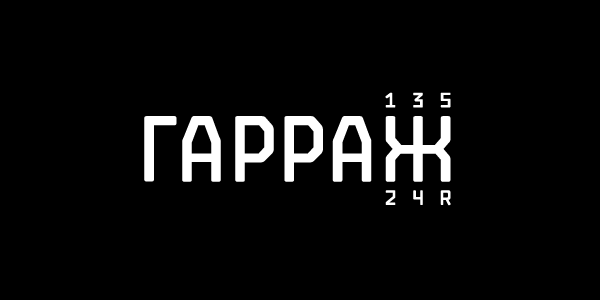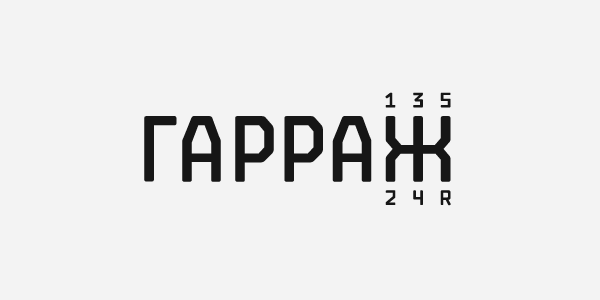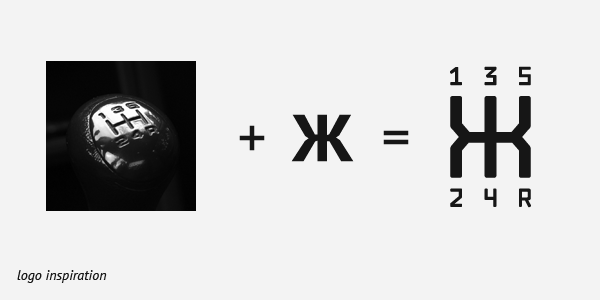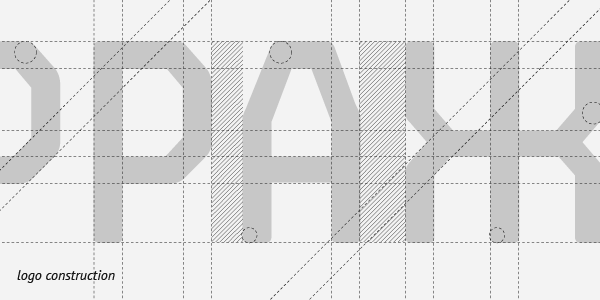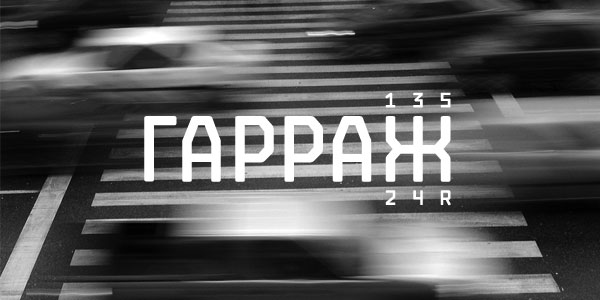
Гарраж
Логотип для пермского автомобильного сайта. Симметричная кириллическая «Ж» оказалась удивительно похожей на коробку передач, оставалось только развить эту графику в модульном, жёстком шрифтовом решении.